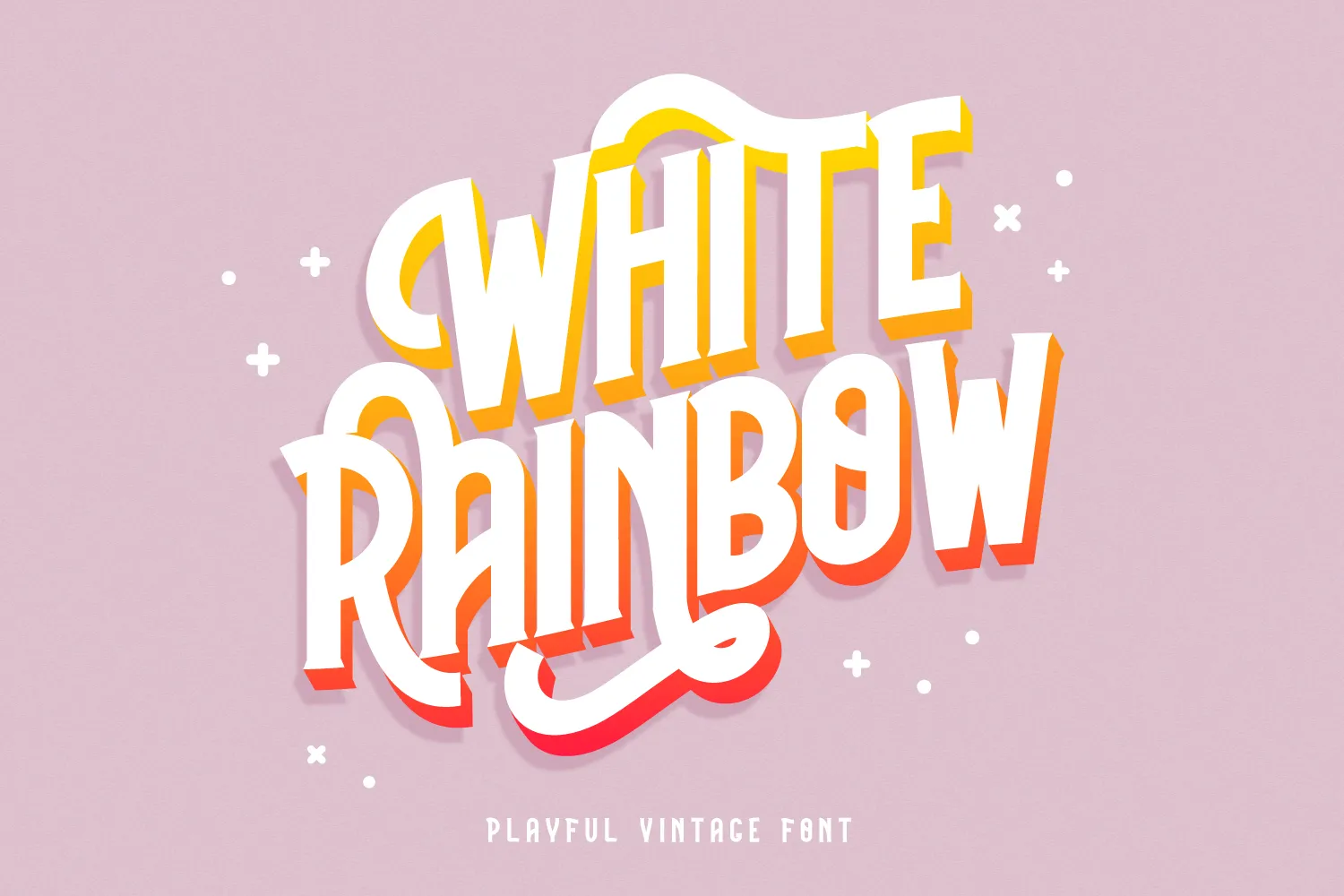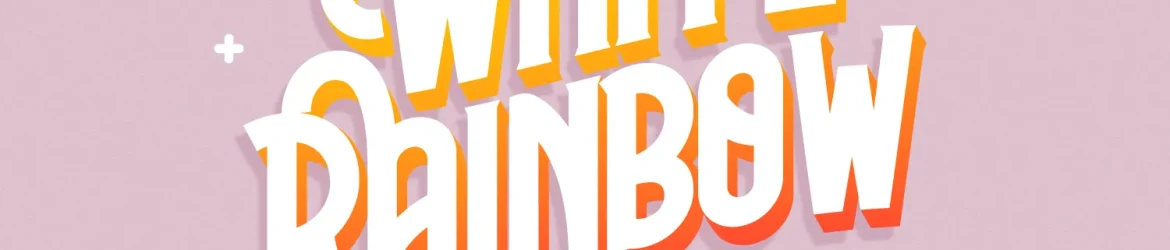
Aqui está uma descrição em português para a página de download da fonte ‘White Rainbow Font’, mantendo os requisitos fornecidos: Esta é uma bela e bold font de display vintage, ideal para texturas retro e nostálgicas que adicionam um toque único ao seu design. Com suporte PUA (Unicode Private Use Area), esta fonte permite a você acessar facilmente todos os símbolos e swashes disponíveis em sua versão completa. Ideal tanto para uso em layouts vintage quanto para criar elementos gráficos interessantes, a White Rainbow Font é uma escolha perfeita para designers que valorizam estilo e funcionalidade. Com seu design elegante e arquitetado sobretudo para texturas e efeitos vintage, esta fonte oferece opções versáteis que podem ser usadas em uma variedade de aplicações gráficas, como logotipos, materiais de marketing ou até mesmo ilustrações. O designer Heloyud criou um design cuidadosamente pensado para proporcionar uma experiência de uso fluida e agradável, sem qualquer perda na qualidade ou funcionalidade. Adicione esta fonte ao seu conjunto e deixe sua criação se destacar ainda mais com elementos vintage e modernos.